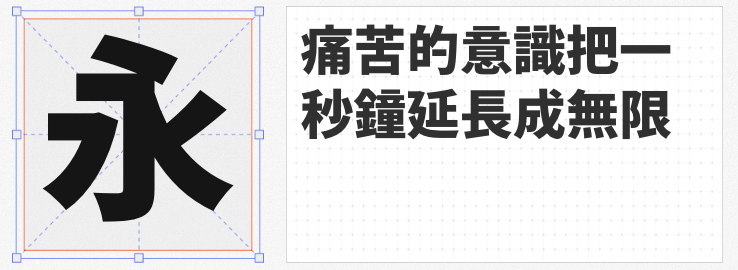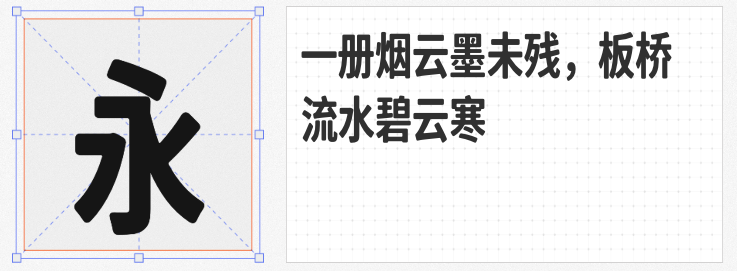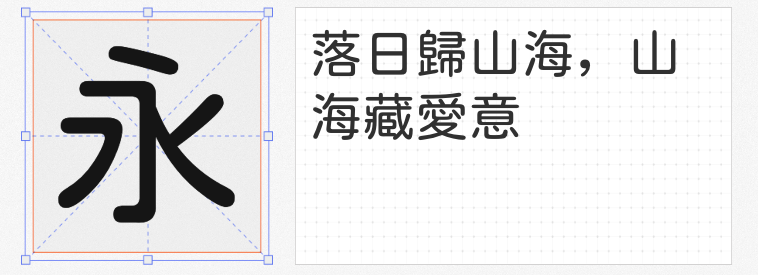
在商业设计中,黑体因其简洁、现代、易读的特点,成为品牌标识、数字界面、印刷品等领域的首选字体。以下四款免费商用黑体各具特色,既能满足基础排版需求,又能为设计注入独特个性。
寒蝉全圆体以日本开源字体小杉圆体、justfont粉圆及猫啃糖圆体为基底,通过调整笔画弧度与字间距,打造出兼具黑体简洁性与圆体亲和力的独特字形。其笔画饱满圆润,转折处自然过渡,弱化了传统黑体的锐利感,更适合传递温暖、柔和的品牌调性。
句读黑体Hant Heavy以更纱黑体、思源黑体为核心,融合尙古黑体、Noto Traditional Nushu等开源字体,形成覆盖47种语言的超广字符集,支持阿拉伯文、泰文、格鲁吉亚文等复杂文字系统。其字形结构严谨,笔画粗细均匀,重字重(Heavy)设计强化了标题的视觉冲击力,尤其适合跨国企业品牌手册、多语言网站及国际化活动的视觉设计。TrueType格式的兼容性,更确保了其在Windows、macOS及移动端的稳定呈现。
基于思源黑体优化而来的寒蝉云墨黑Compact Bold,通过添加圆角与重构字重比例,在保留黑体简洁性的同时,赋予字形更温润的视觉感受。其笔画粗细过渡自然,字面紧凑但不拥挤,适合长文本排版与小字号场景。
尚古等宽H以思源系列字体为骨架,集成黑体、明体、圆体风格,并通过OpenType特性实现简繁动态转换,解决跨地区排版难题。其等宽结构确保了代码、数据表格的规整性,而灵活的标点规范(支持TC/SC/JP)则满足了古籍数字化、文化类APP等场景的需求。
这四款免费商用黑体,从亲和圆润到多语言兼容,从排版优化到文化融合,覆盖了商业设计的多元需求。设计师可依据项目调性自由选用,为作品注入专业与创意的双重价值。